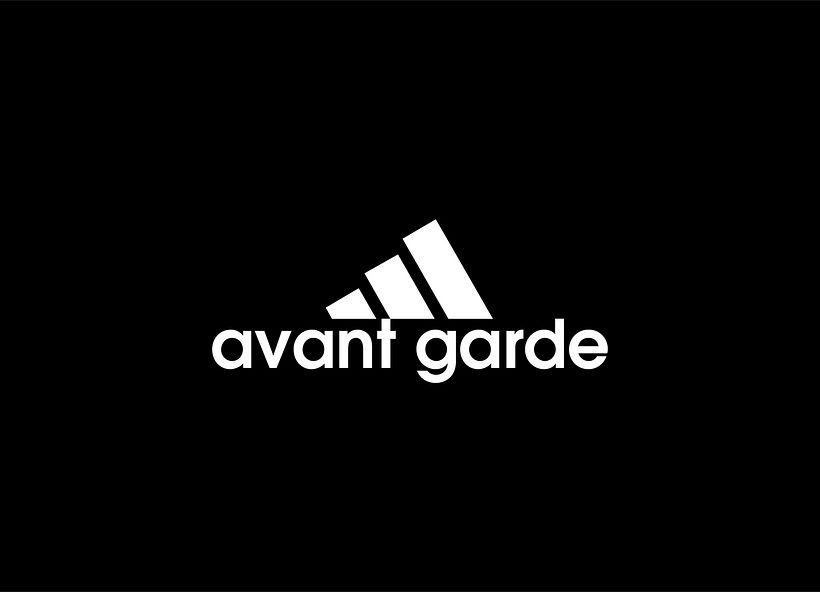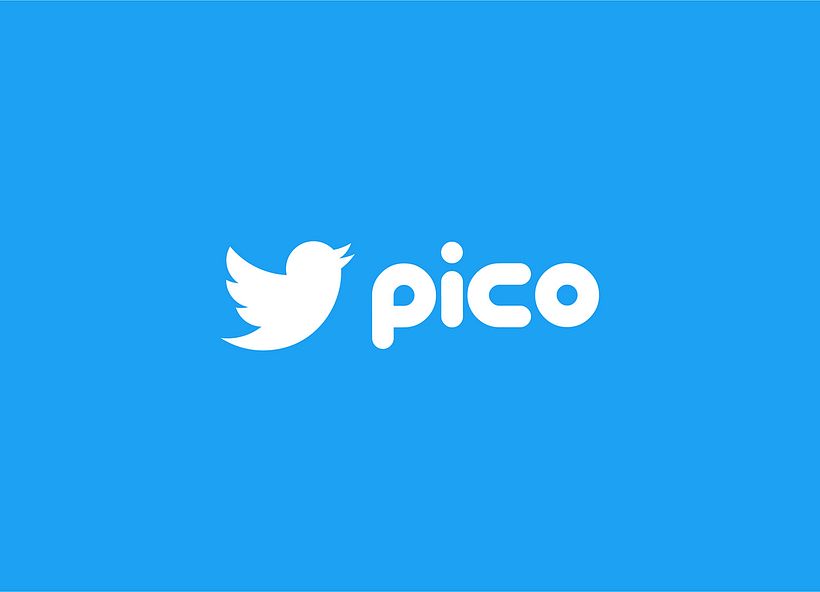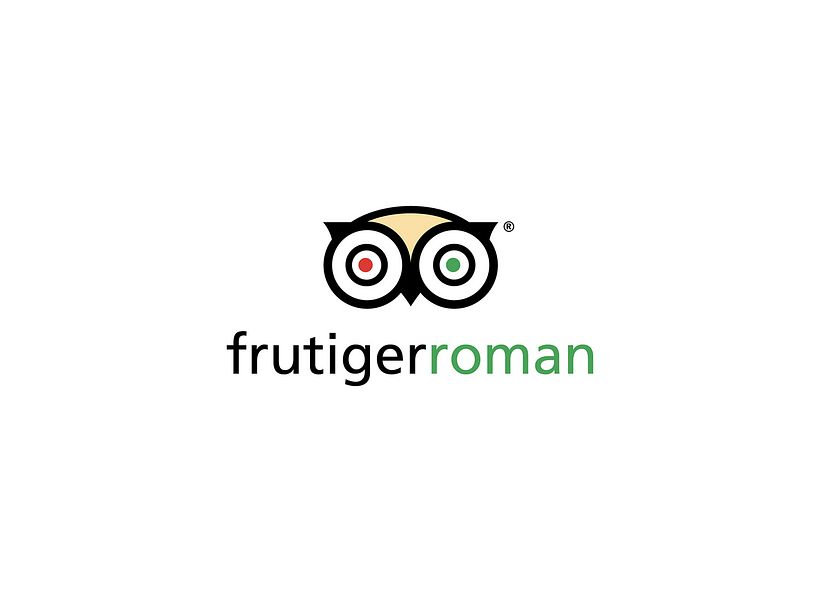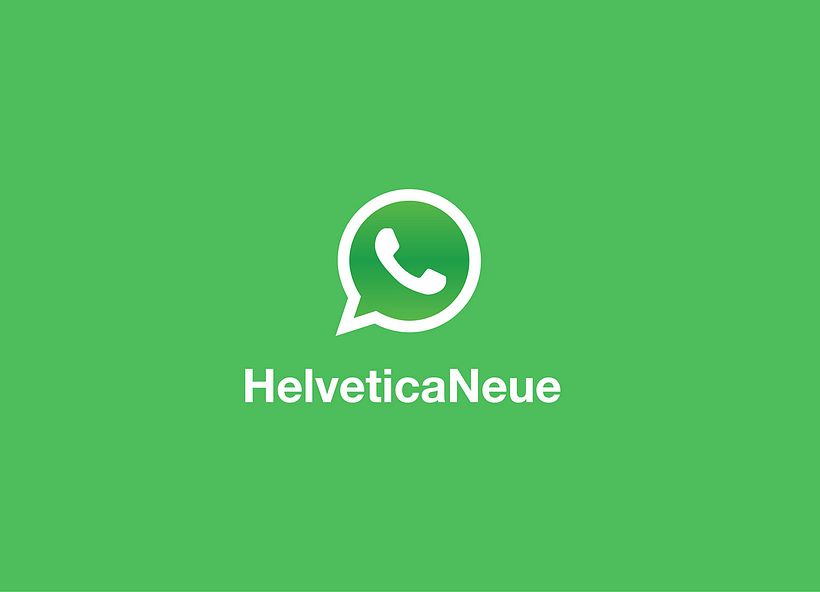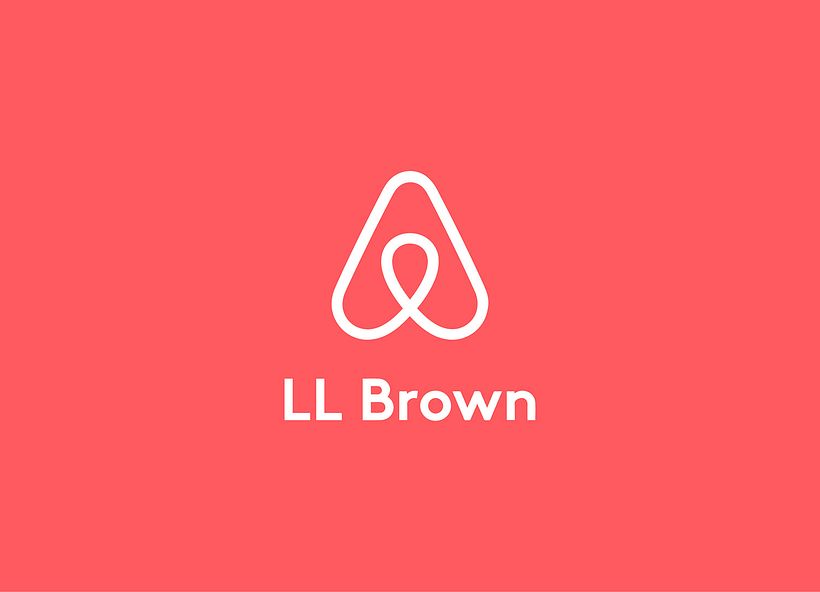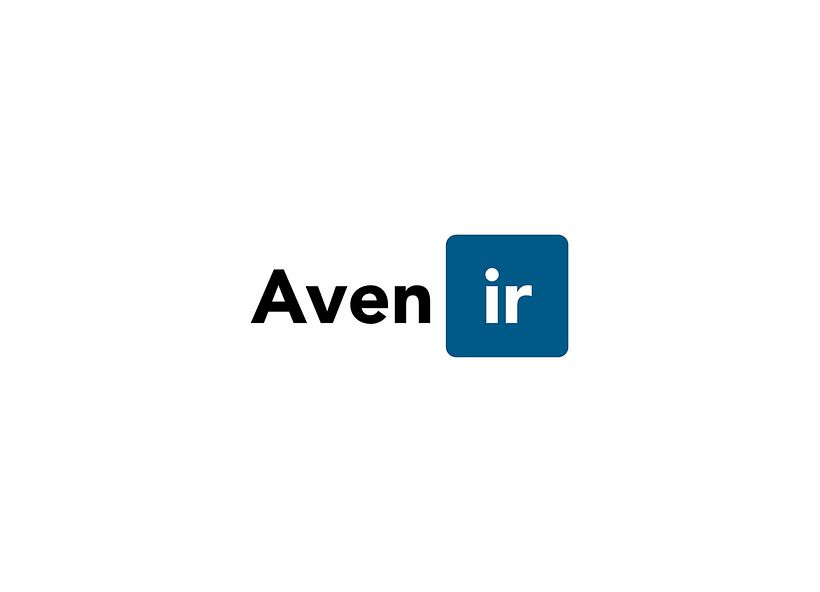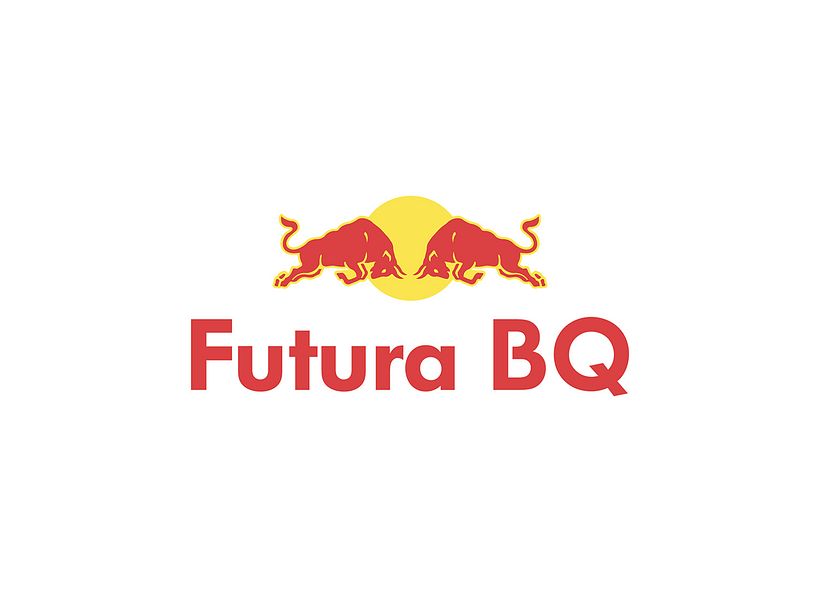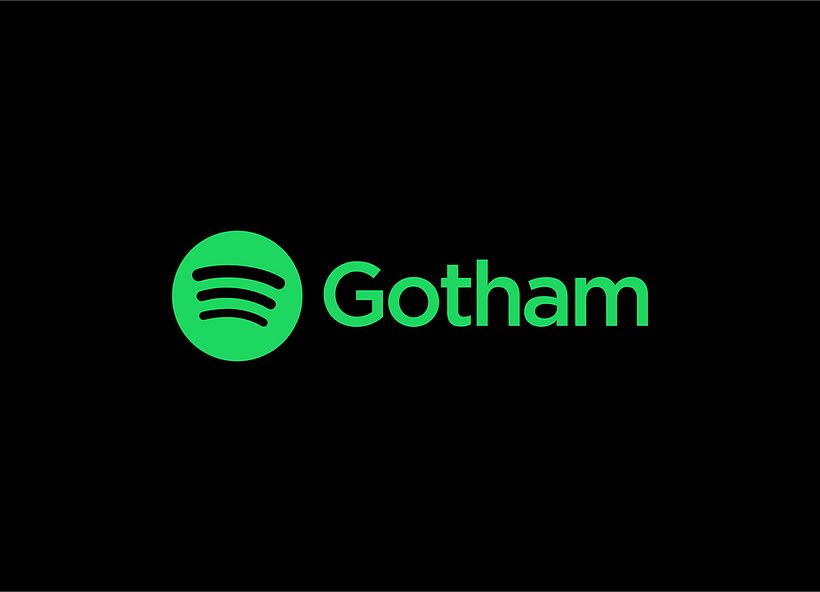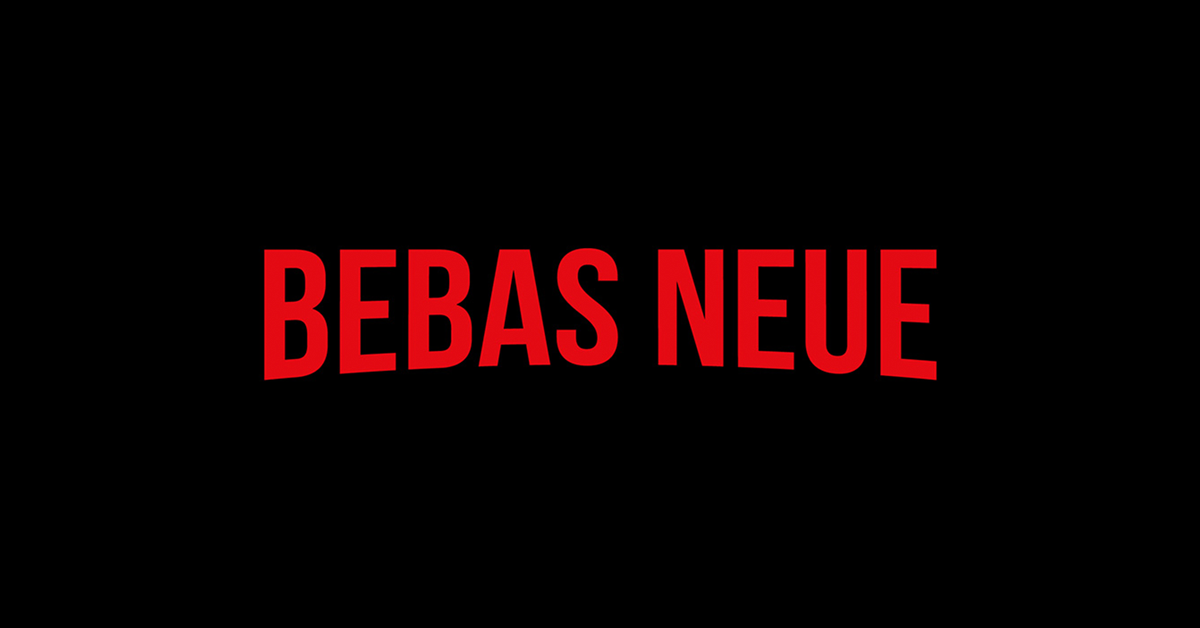
¿Qué tipografías usan los logotipos más famosos?
Es una pregunta que, probablemente, te habrás hecho muchas veces y en el proyecto de este italiano está la respuesta.
En cualquier proyecto de diseño la elección de la tipografía es un asunto de extrema importancia, más aún cuando nos referimos a un logotipo en el que la fuente tiene gran protagonismo. El diseñador italiano Emanuele Abrate, como tantos otros diseñadores hacen cada día, se preguntó infinidad de veces cuáles eran las tipografías utilizadas en algunos de los logotipos más famosos, en aquellos que vemos cada día y, después de una ardua investigación, decidió dar forma a Logofonts, un proyector que nos muestra estos logotipos en los que los nombres de los productos han sido cambiados por los nombres de las tipografías usadas para diseñarlos.
Marcas y logotipos que nos acompañan diariamente como Facebook, Twitter, Whatsapp, Adidas, Netflix o Instagram son los grandes protagonistas de Logofonts, un proyecto en el que Emanuele Abrate nos descubre que el clásico logotipo de Nike, por ejemplo, fue creado con una tipografía no menos clásica: Futura. Y que Adobe usa Myriad, la tipografía sans serif diseñada por Robert Slimbach y Carol Twombly para la compañía, que se convirtió también en la fuente corporativa de Apple a principios del siglo XXI.
De Logofont destaca también la manera en que su creador integra los nombres de las tipografías en los logotipos y como estos, a pesar de no contener el nombre del producto que representan, son 100% reconocibles.